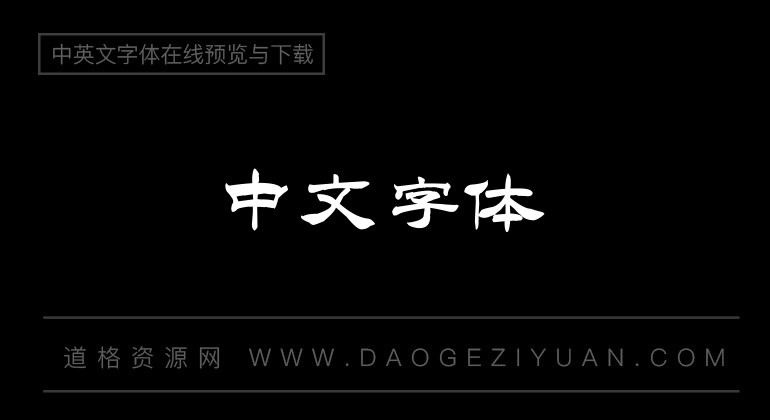
于洪亮毛笔隶书简体
于洪亮毛笔隶书简体是一款古典风格的毛笔字体,以颜色深沉、笔画流畅、结构完整、细腻精致而著称。该字体源于古典书法,每一笔画都经过精心设计,使字体看起来更加立体,更有质感。这款字体拥有良好的可读性,适合用于品牌宣传、文字排版、书法等多种场景。
于洪亮毛笔隶书简体是一款非常不错的手写艺术字体,具有很好的视觉感,适合于文化类的宣传设计、商业类品牌的广告和产品包装设计以及个性化文字排版等较多场景。